Grundschrift
1. Grundschrift bei Druckschriften und Screen Fonts
In der Typografie ist die »Grundschrift« der Schriftschnitt einer Schriftfamilie oder Schriftsippe, der innerhalb eines geschlossenen Schriftsatzes, beispielsweise einem Buch, einem Geschäftsbericht, einer Website, einer Anzeige oder eines Prospekts, als Primärschrift (Basisschrift) verwendet wird. Vereinzelt auch als »Fließtextschrift« oder »Lauftextschrift« und im gewerbespezifischen Sprachschatz deutscher Schriftsetzer und Drucker von Offizinen aus der Periode des materiellen Handschriftsatzes (Bleisatz) als »Brotschrift« bezeichnet.
In der Lesetypografie besteht die Grundschrift, z.B. für einen Buch, eine Zeitung, ein Magazin oder eine Website, in der Regel aus einer gut lesbaren Textschrift (siehe Lesbarkeit) im Schriftschnitt »Normal« (regular, normale, chiaro tondo, font-weigt 400) bzw. im Schriftschnitt »Buch« (book, romain labeur, libro).
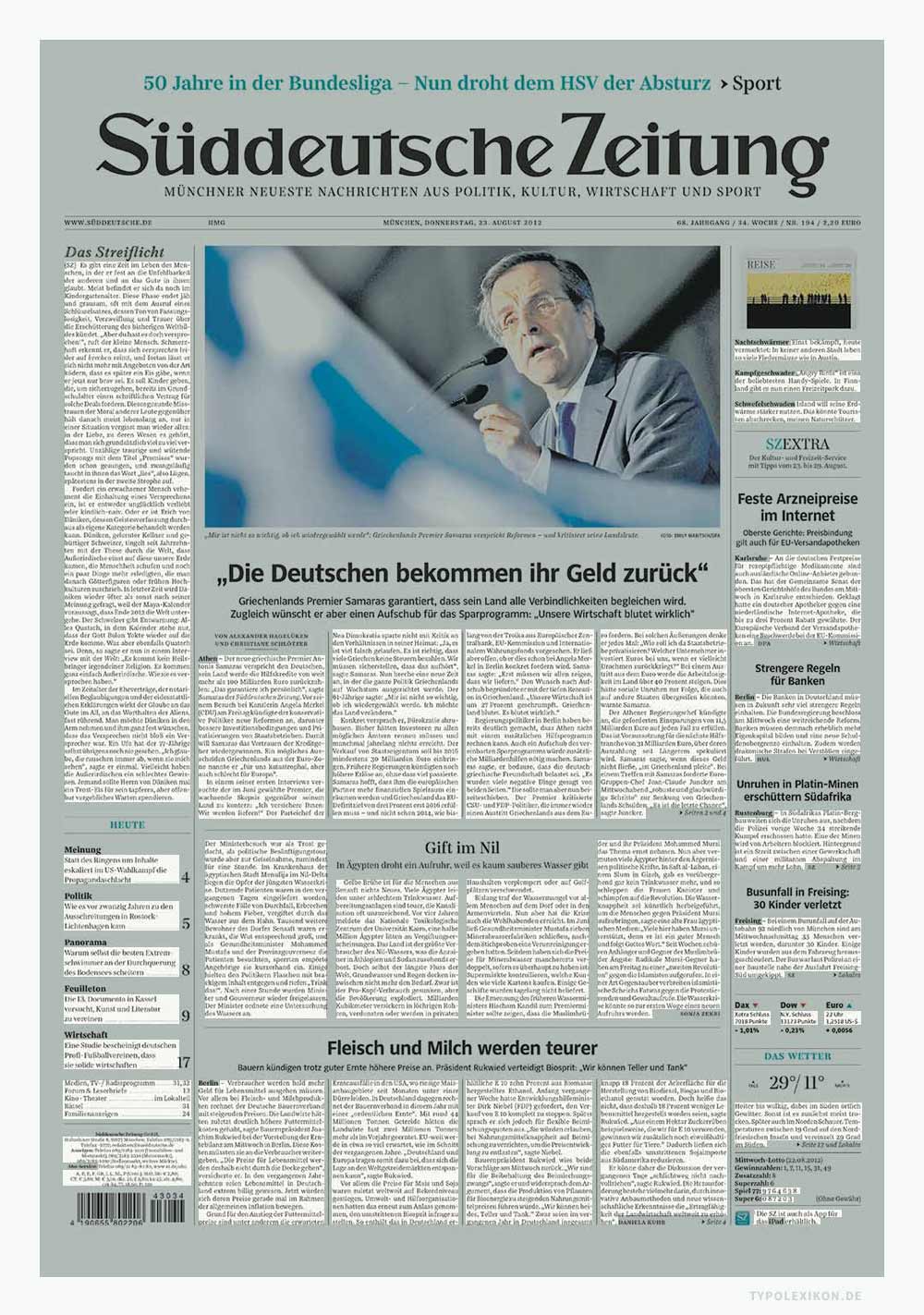
Die Wahl der Grundschrift auf den Taxonomieebenen der Hauptschriftgruppen (z.B. Antiqua), Schriftuntergruppen (z.B. Klassizistische Antiqua) und Nebenschriftgruppen (z.B. Bodoni-Varianten) gehört in den Bereich der Makrotypografie. In der Mikrotypografie entscheidet man sich dann für eine bestimmte Variante, z.B. eine »Bauer Bodoni Roman« von Heinrich Jost (1889–1948) und Lois Höll (1860–1935) aus der Linotype®-Schriftenbibliothek (siehe Schriftklassifikation).
Die Grundschrift ist grundsätzlich immer die Primärschrift (Basisschrift) eines Schriftsatzes, eines Schriftsystems oder eines Corporate Designs (Hausschrift). Die Typometrie, die Hauptschriftlinien und die mikrotypografische Zubereitung der Grundschrift dienen als Grundlage für die Wahl und Abstimmung aller weiteren verwendeten Schriftstile und Schriftarten. Von ihr leiteten sich sämtliche innerfamiläre und extrafamiliäre Schriftmischungen ab, beispielsweise für Headlines, Bildunterschriften, Fußnoten, leise und laute Auszeichnungen.
Bei der Schriftwahl – egal ob für den Mengenschriftsatz (Werksatz, Zeitungssatz), den Titelsatz (Akzidenzsatz), eine Copy oder für ein Corporate Design – wird grundsätzlich immer zuerst die Grundschrift für eine semantisch-typografische Auszeichnungsmatrix gewählt, dann folgen die innerfamiliären Auszeichnungsschnitte und schlußendlich die extrafamilären Schriftstile (siehe auch Schriftwahl).
2. Grundschrift bei Schulschriften
Als »Grundschrift« wird seit 2011 eine Variante der schulischen Druckschrift (Lateinische Ausgangsschrift (LA), Vereinfachte Ausgangsschrift (VA), Schulausgangsschrift (SAS)) für Grundschüler bezeichnet, welche im Auftrag des Grundschulverbandes 1) entwickelt wurde und von interessierten deutschen (Grund)Schulen erprobt werden kann. Das Projekt ist in Fachkreisen umstritten.